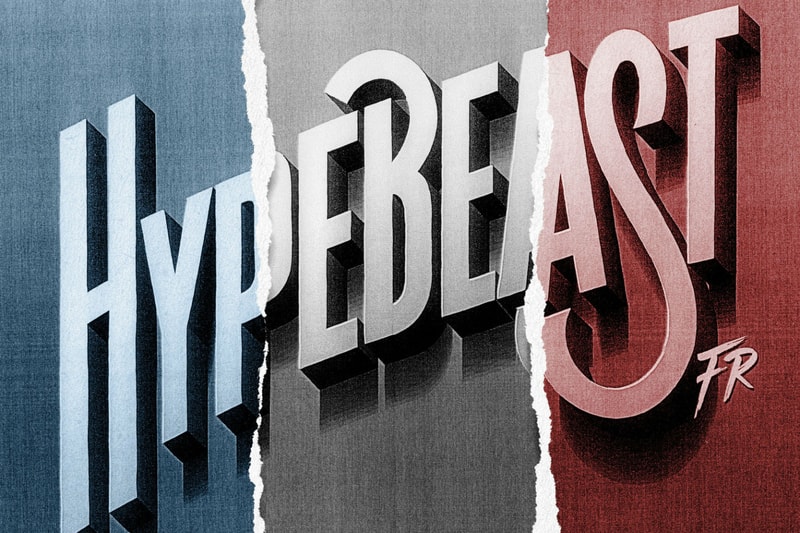
En un tour de magie le talentueux Tyrsa alias Alexis Taieb a sorti de son chapeau, son art du lettrage afin de souhaiter la bienvenue à HYPEBEAST France.
En effet Tyrsa a travaillé la typographie à la main qu’il a ensuite scanné sur un ordinateur puis s’est rendu dans un cyber café afin d’obtenir cette texture à l’ancienne.
Reconnu comme l’un des plus grands typographe de sa génération, Tyrsa a débuté sa carrière en 1999, il a fait ses premières armes dans le graffiti puis passionné des lettres et des formes il intègre l’école des Gobelins et en sort diplômé en 2007.
Aussi à l’aise sur papier que sur ordinateur, Tyrsa réinvente les lettres de manière artistique et esthétique, il a en autre travaillé pour de grandes agences et marques prestigieuses comme publicis, DDB, Nike ou Carhartt.